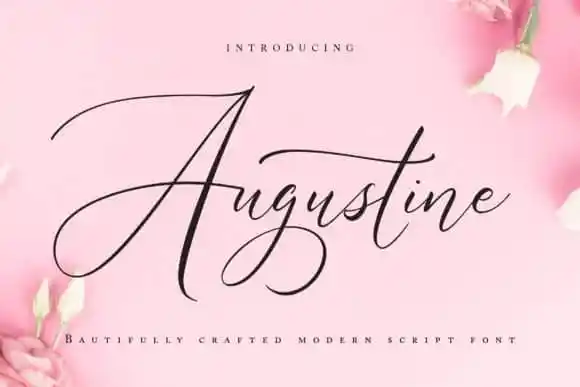
Augustine Calligraphy Font – Download Grátis
Introduzimos a Augustin Script Calligraphic Font, uma elegante tipografia moderna com estilo nóvio. Este é um tipo fino clássico que ganha vida com sua abordagem íntegra. Esta fonte conta com várias modernas curvas para tornar seus trabalhos elegantemente sofisticados e perfeitos, adquirindo um toque de elegância e suavidade ao mesmo tempo. Ideal para quem busca agregar uma dose de elegância a qualquer projeto criativo, Augustin Script está disponível em diferentes modos de curvatura moderna, permitindo que você personalize o estilo conforme necessário. Essa fonte é perfeita tanto para designers profissionais quanto para aqueles iniciantes no campo da design visual, oferecendo uma ferramenta versátil e criativa para explorar novas possibilidades gráficas.